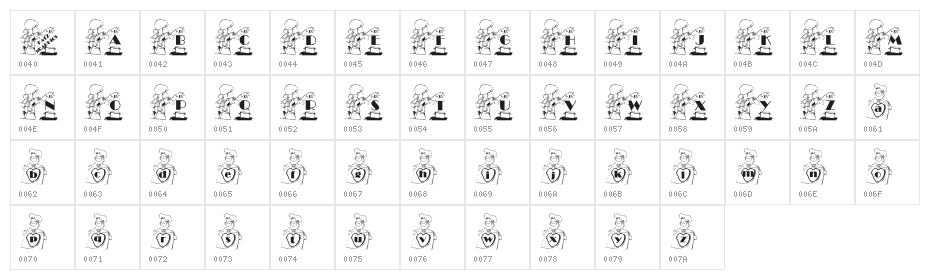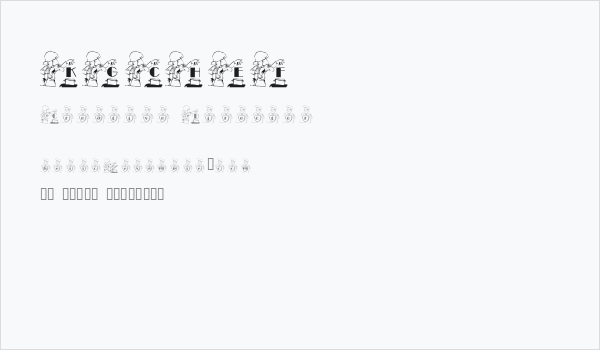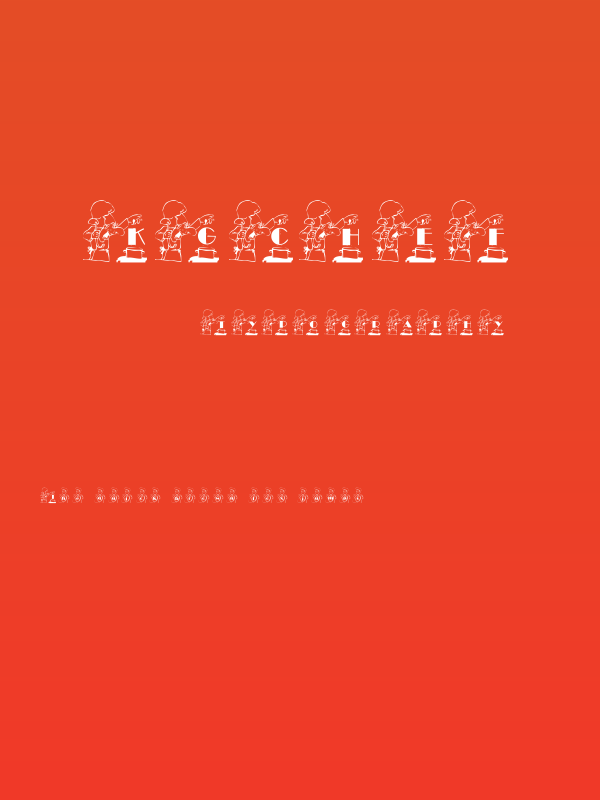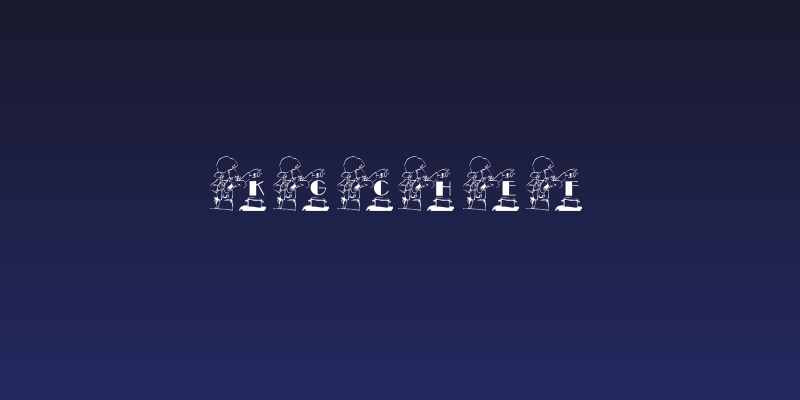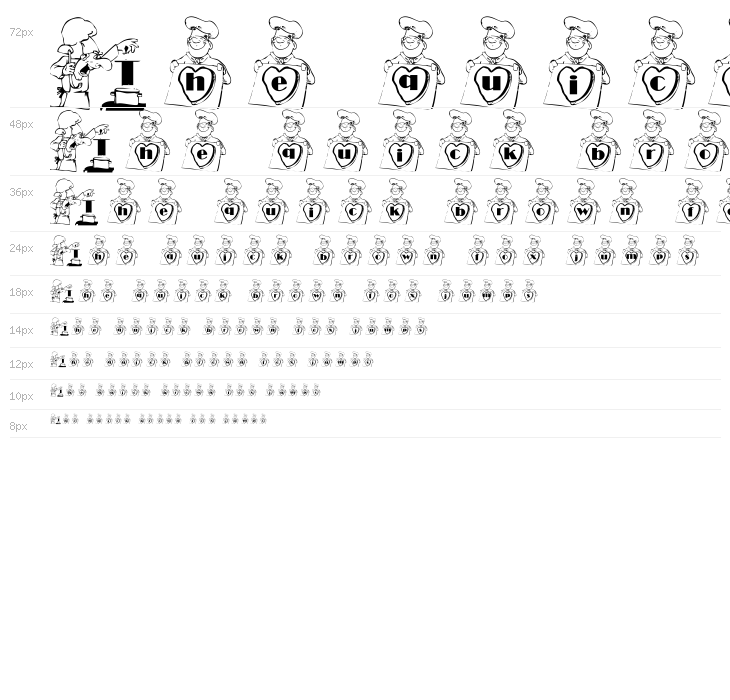
KGCHEF Font
| Anwendungsfall | Logos, Headlines, Thematic designs |
| Vorgeschlagene Projekte | Ideal for culinary-themed projects, children's books, playful branding, or restaurant menus. |